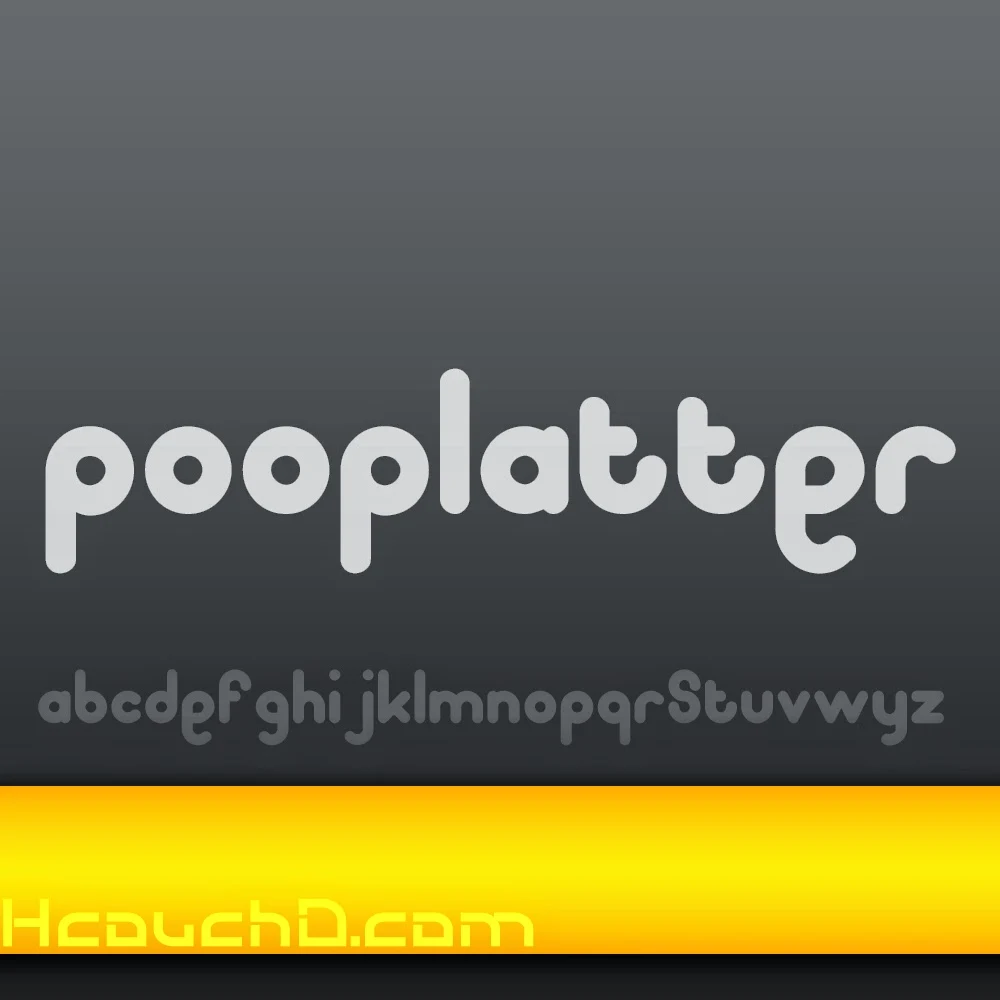
خط Pooplatter جميل ، و سبق أن استعملناه في درس ” درس 39 : كيفية عمل تأثير النص حلوى قصب العيد في فوتوشوب + الملف PSD و الخط ” ، يمكنك تحميل هذا خط من رابط أسفله …